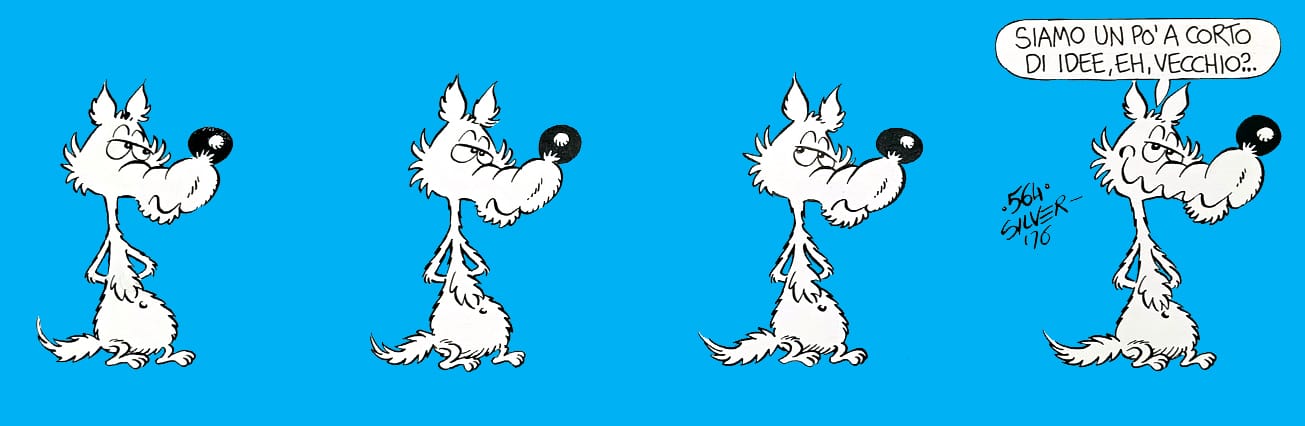
Questo mese mi sono ritrovato a fare più attenzione a quello che di solito resta dietro le quinte.
Ho visitato la mostra dedicata a un personaggio leggendario che avevo smesso di leggere: soffermarmi sulle tavole originali mi ha ricordato perché lo avevo amato così tanto.
Sono tornato ai video di un maestro sign painter: dietro la sicurezza del gesto si intuisce tutto il peso dell’esercizio quotidiano.
Ho riaperto un libro che prendeva polvere in libreria e ho riscoperto il lavoro di designer fondamentali per la grafica italiana.
Infine, in tipografia, ho passato del tempo con gli stampatori, cercando di collegare in modo più preciso quello che progetto al computer con quello che poi prende forma reale.
In tutti questi passaggi, la cosa interessante non è solo il risultato finale, ma anche quello che lo rende possibile.
LUPO ALBERTO - L'eroica fifa blu
Pordenone, Palazzo del Fumetto – Dal 8 novembre 2025 al 3 maggio 2026
Lupo Alberto è uno di quei personaggi che hanno segnato profondamente l’immaginario collettivo italiano: molto più stratificato, attuale e incisivo di quanto possa sembrare a un primo sguardo. Anche per questo il Palazzo del Fumetto di Pordenone gli ha dedicato una grande retrospettiva, a oltre cinquant’anni dalla prima striscia del 1974.
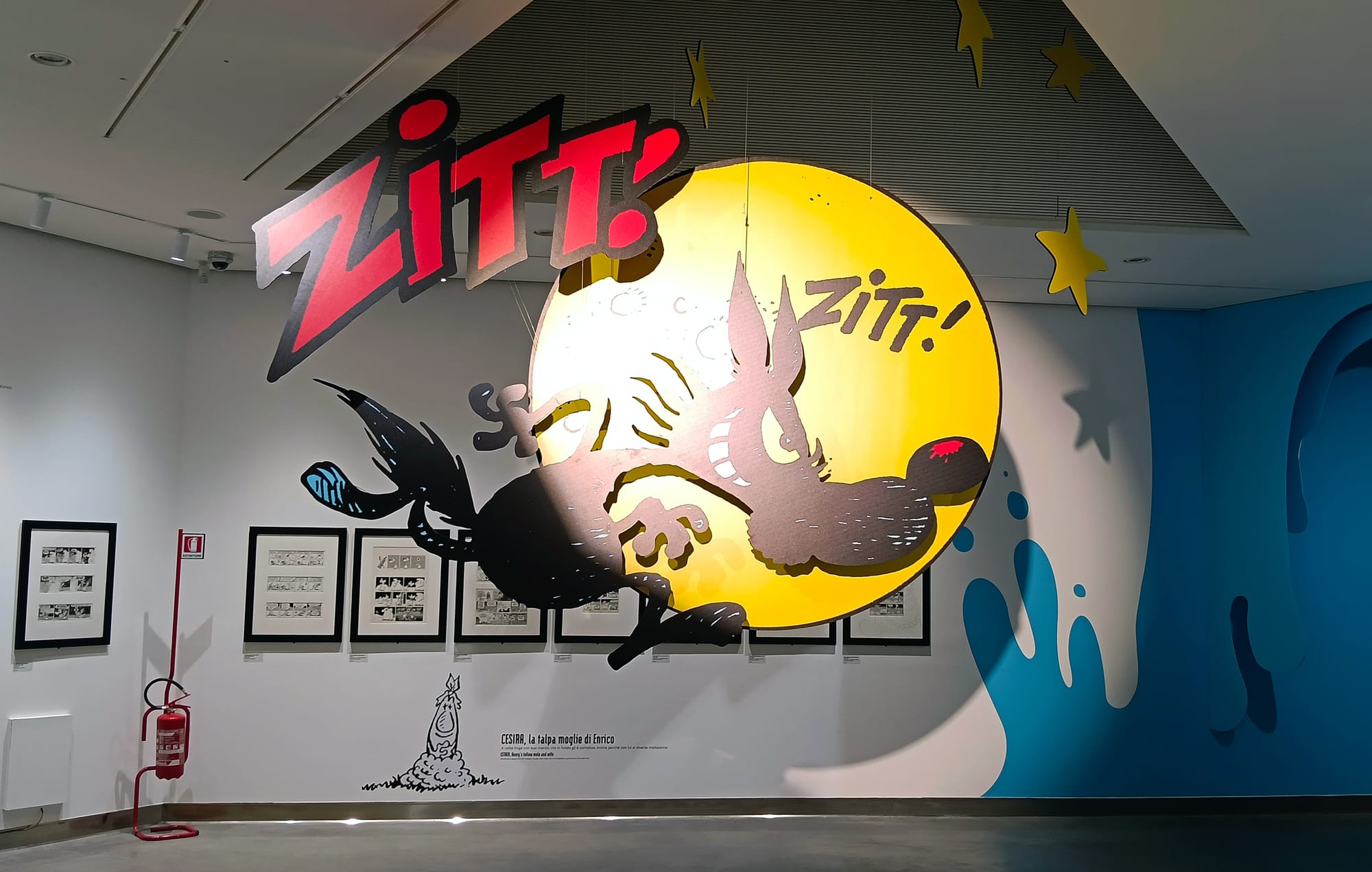
Silver — pseudonimo di Guido Silvestri — è il creatore di Lupo Alberto. Giovanissimo entra nella bottega di Bonvi, il padre delle Sturmtruppen, che ne riconosce il talento e lo spinge alla pubblicazione: il debutto è previsto nel 1973 sulla rivista Undercomics, ma la testata non va oltre il numero zero.
L’esordio vero arriva l’anno successivo sul Corriere dei Ragazzi, dove un redattore — Alfredo Castelli — decide di cambiare il titolo originale pensato da Silver, La fattoria McKenzie. E così, anche grazie all’intuizione di due grandi maestri del fumetto italiano, nasce Lupo Alberto.
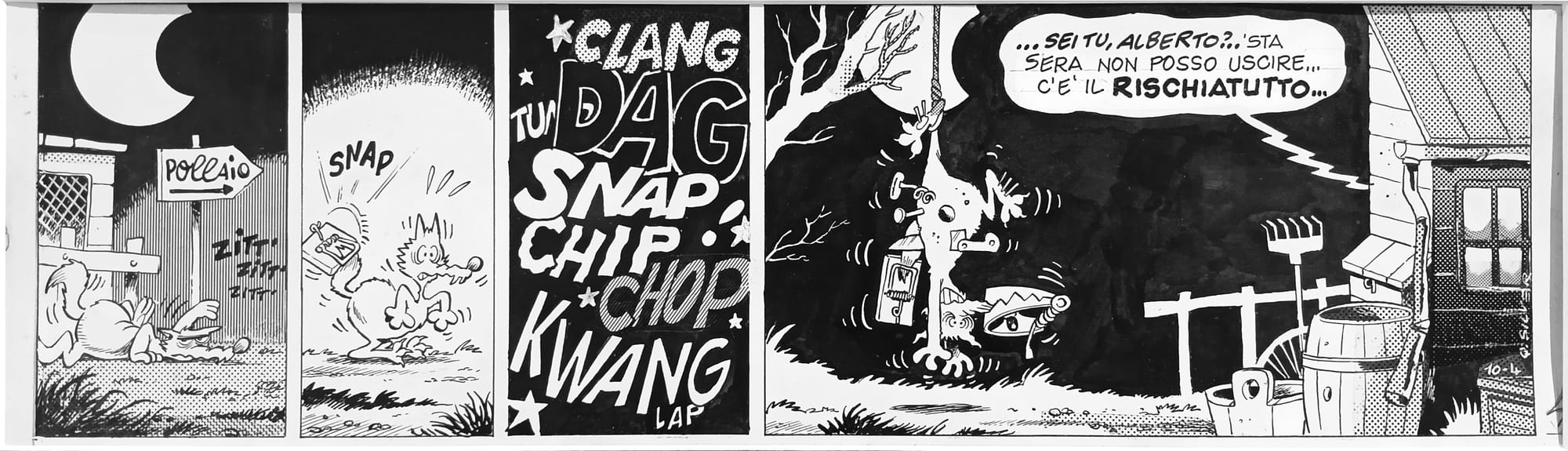
Lo stile grafico del lupo è inizialmente debitore dei cartoni animati di Hanna-Barbera, così come della comicità slapstick. Ma affiorano anche rimandi ad autori seminali come Benito Jacovitti e Charles Schulz, evidenti nella costruzione del meccanismo comico e nell’uso, maturo e originale, delle onomatopee (il celebre ZITT ZITT di Lupo Alberto riecheggia certe invenzioni di Cocco Bill).
Col tempo, però, Silver evolve il suo segno: si fa più consapevole e maturo, e si muove con disinvoltura tra formati diversi — dalle strisce alle tavole, fino alle brevi storie che chiama Novelas. Il tratto comune resta la comicità: caustica ma mai volgare. Intorno al lupo e ai suoi comprimari, la fattoria McKenzie diventa un microcosmo che somiglia fin troppo alla società italiana.
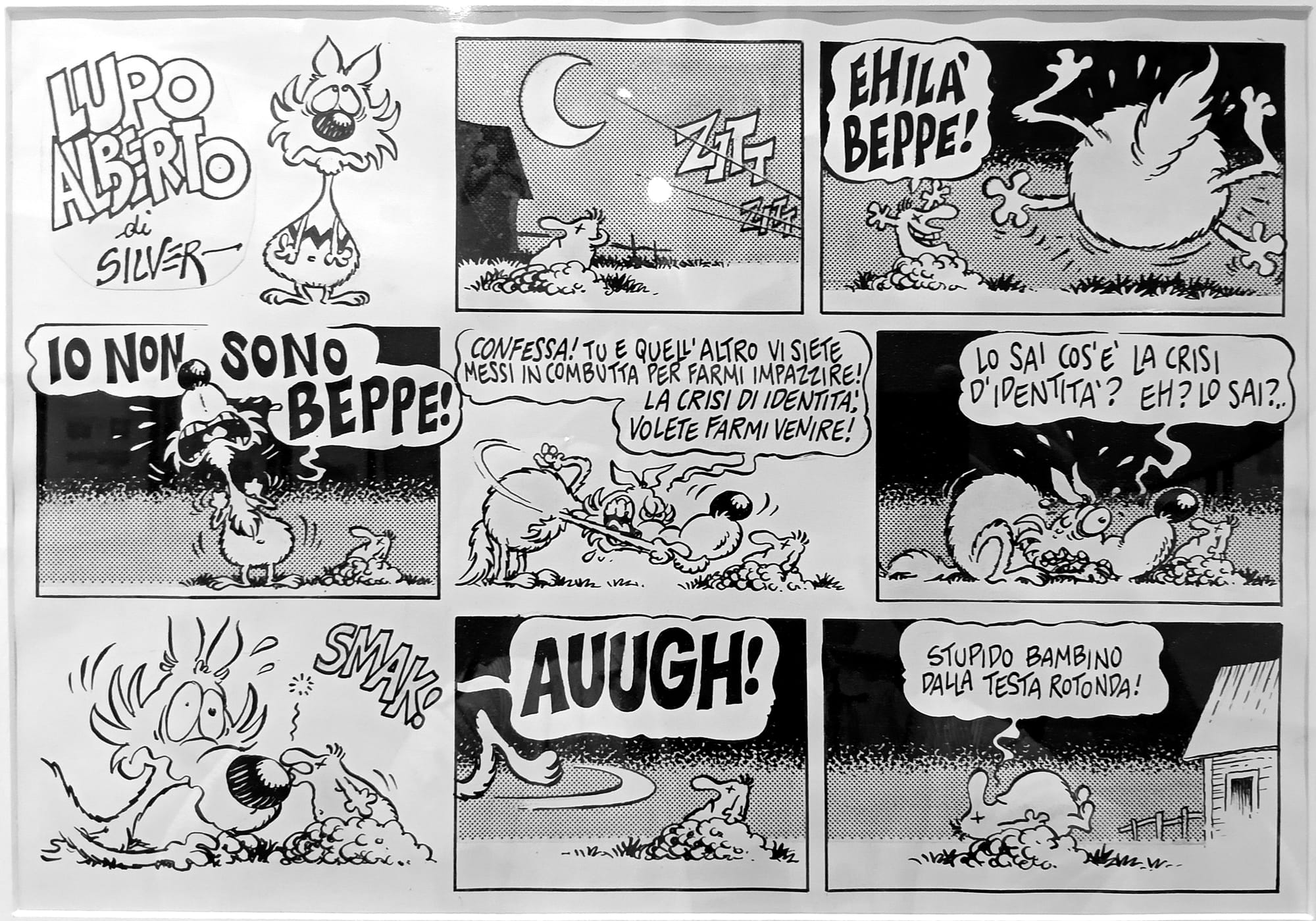
Sì, perché lo sguardo di Silver affonda davvero nella società e – in modo quasi sorprendente – riesce a descriverla, provocarla, prendere posizione, senza mai risultare ideologico o fuori luogo, anzi strappando un sorriso che a volte ha anche un retrogusto amaro.
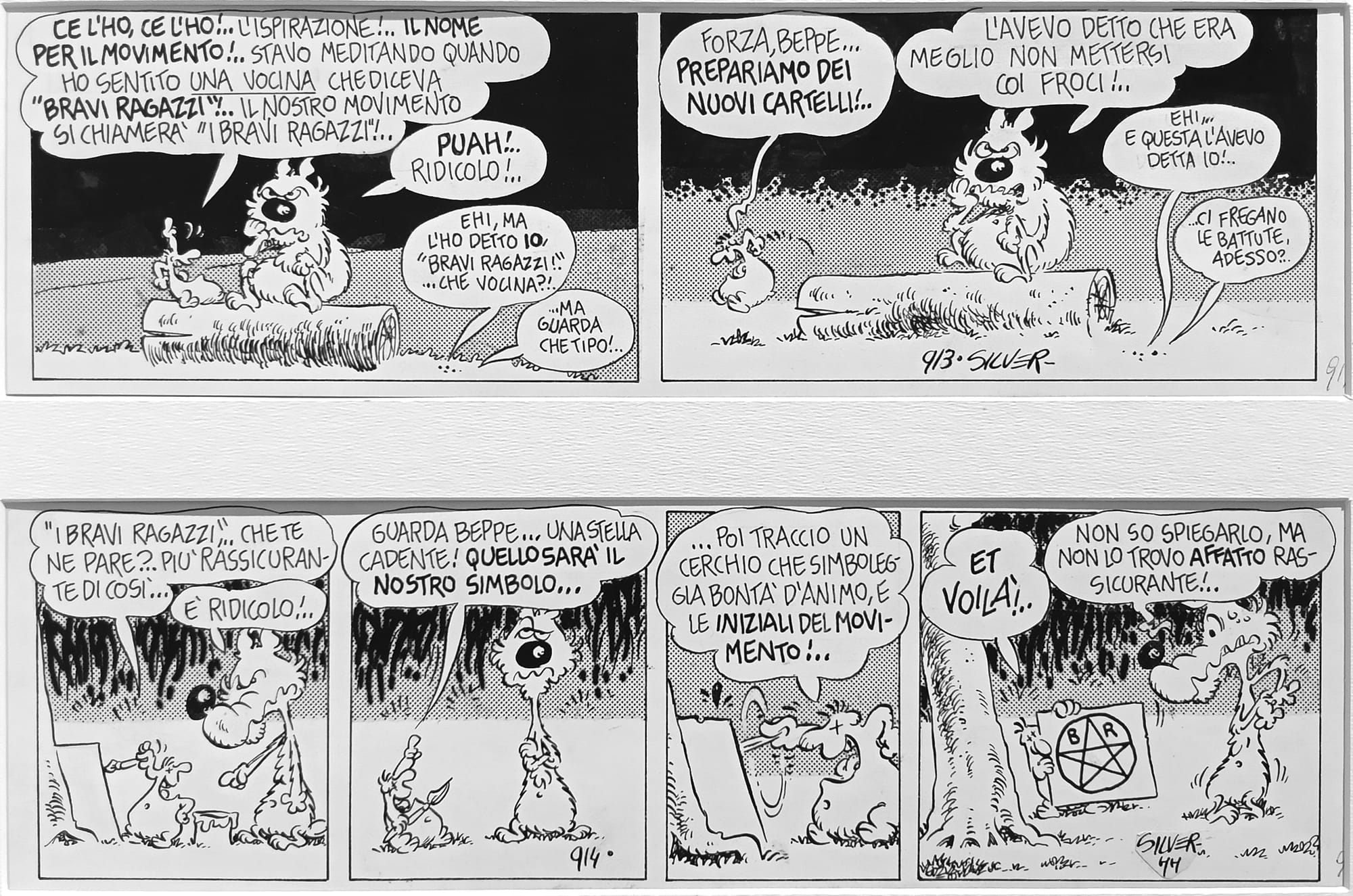
La mostra si sviluppa nelle ampie sale del Palazzo del Fumetto e dà spazio anche alle molte declinazioni del Lupo: dai numerosissimi gadget alle campagne sociali di cui è stato volto e portavoce, fino ai contributi di altri autori che lo hanno reinterpretato e immaginato.
Da anni nutro una profonda fascinazione per il sign painting e per quegli artigiani capaci di progettare una scritta — o un’insegna — e poi dipingerla a pennello.
Tra i migliori, per me, c’è John King: ho passato ore a osservare i suoi gesti, precisi e armoniosi, da cui traspare uno stile personale e riconoscibile.
Il video che vi segnalo è la presentazione di
uno dei suoi corsi
— che ho seguito — e che mi ha dato strumenti preziosi per comprendere la costruzione delle lettere maiuscole.
Alle radici della comunicazione visiva italiana
Autore
Heinz Waibl
Editore
Centro Cultura Grafica Como
Prima edizione
1988
Pagine
368
Questo libro nasce da una tavola rotonda sul tema La grafica oggi, tenutasi a Como nel 1985, con la partecipazione di designer del calibro di Max Huber, Roberto Sambonet e Heinz Waibl. Proprio una presentazione di Waibl, accolta con grande interesse, diventa il punto di partenza del volume.
Waibl — eccellente graphic designer — conduce una ricerca paziente e appassionata per evidenziare i protagonisti di un secolo di grafica, accompagnando il racconto con centinaia di splendide riproduzioni.